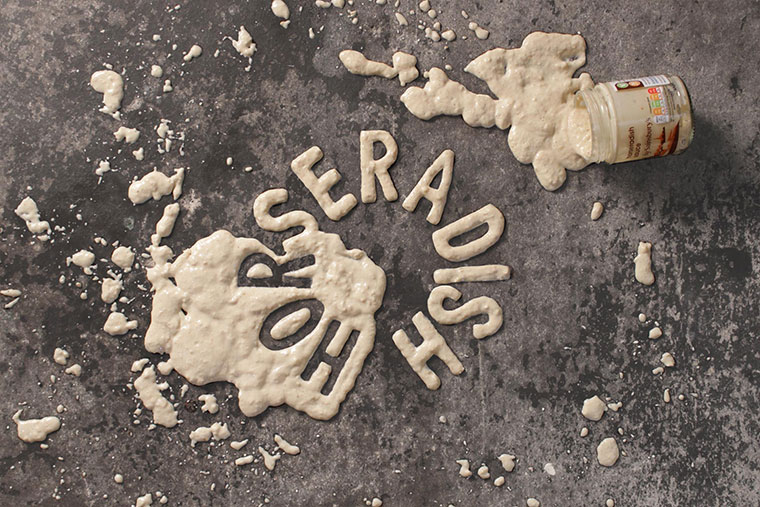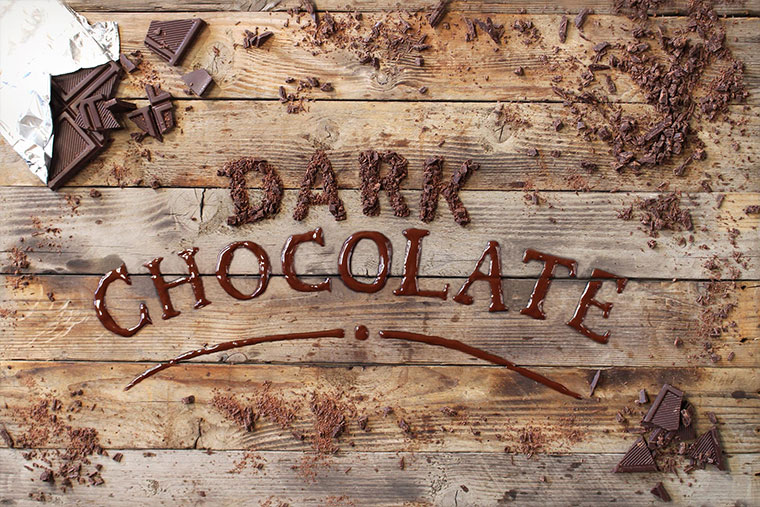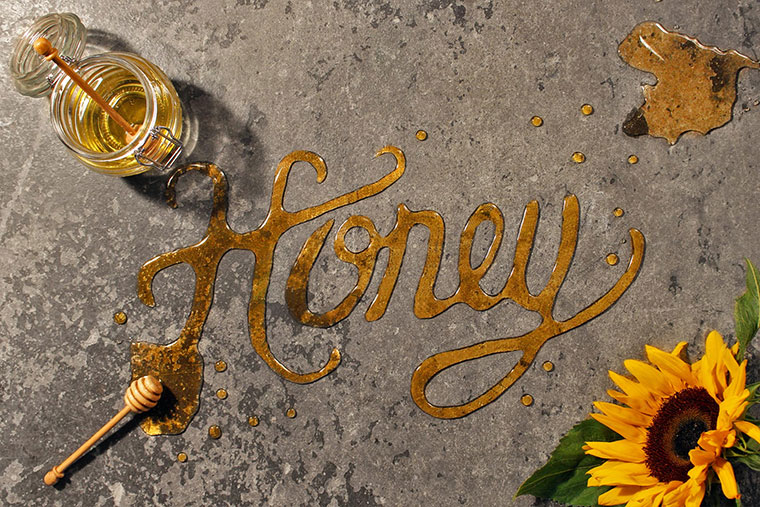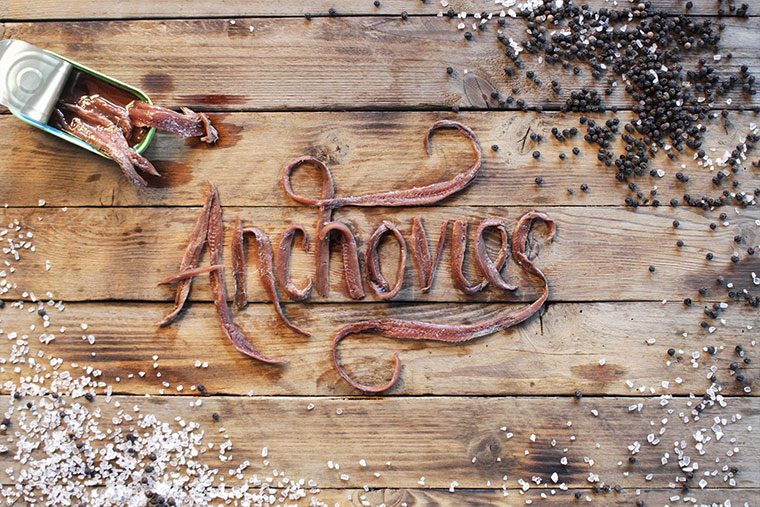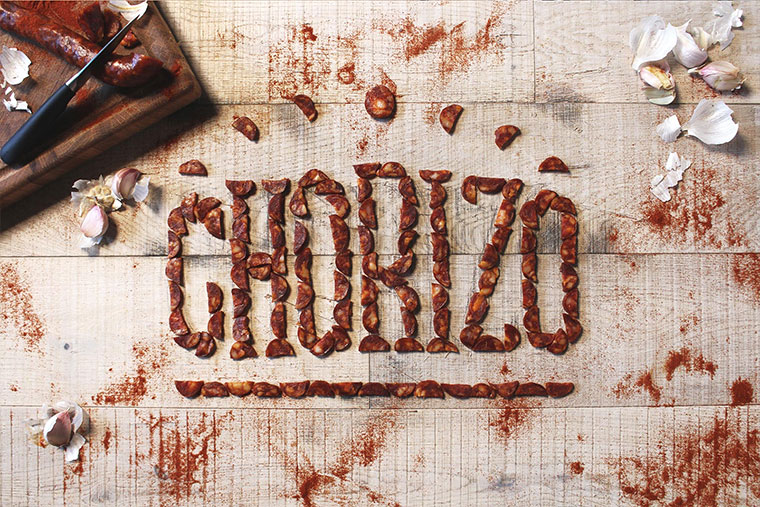
Lecker Food-Typografie
Für die Supermarktkette Sainsbury hat das britische Design Studio Side by Side einige sehr schöne Food-Typografien gezaubert. Passend zum Thema Twist Your Favourites werden Zutaten vermischt, Bestandteile verstreut und am Ende gibt es jeweils zueinander Passendes im Schriftbild. Lecker Design!
„For each design we wanted a connection between the type and the ingredient. We created bespoke lettering and sourced all props and backgrounds, meaning a good few hours rummaging around antique shops (the wooden backgrounds are broken up pallets which were then aged with a blow torch).“
Weitere Informationen zu dieser Arbeit gibt es auf der Website von Side by Side zu sehen. Abschließend noch ein Clip zur Entstehung eines Schriftzuges im Zeitraffer: